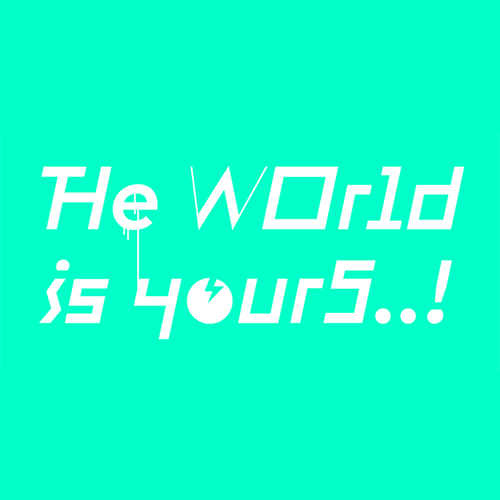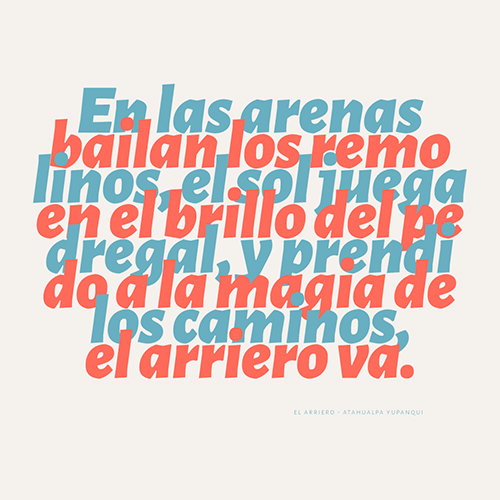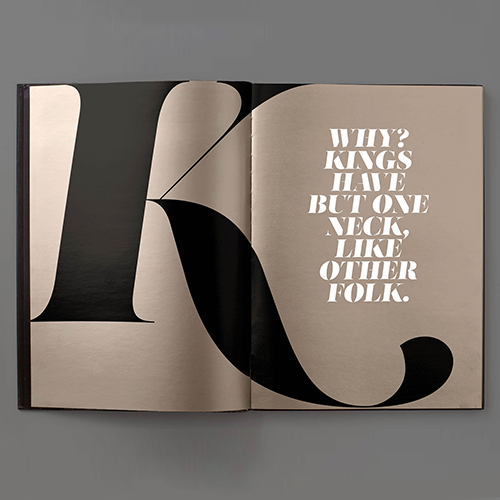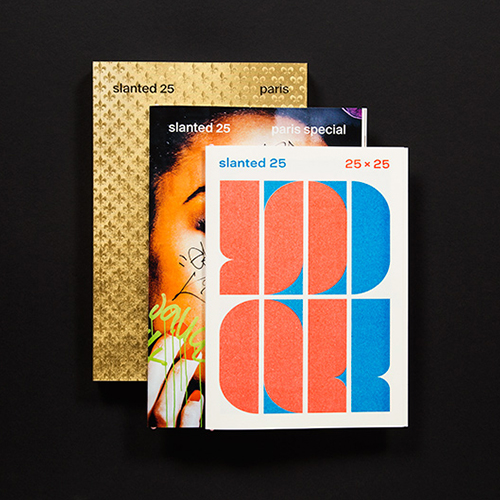
Si teniu pensat passar per la capital, no us perdeu aquesta magnífica exposició on podreu descobrir els millors dissenys tipogràfics de l’any 2015, tant de tipografia aplicada com de disseny de tipus.
La podeu visitar en el marc de Typomad 2015, que se celebra a la Central de Disseny de Matadero Madrid, on s’exposa una selecció de treballs tipogràfics guardonats internacionalment.
La Central de Disseny de Matadero Madrid és un Centre de Creació Contemporània situat a la plaça de Legazpi número 9 de Madrid.
És un espai dedicat exclusivament al disseny en totes les seves formes, on es desenvolupen projectes vinculats al disseny gràfic, el disseny d’interiors i el disseny industrial.
El Matadero disposa d’un ampli espai de referència cultural per a la promoció del disseny i la difusió de propostes i projectes de tota mena.
Aquí es posa en valor la relació entre cultura i economia, integrant-les de manera transversal; així, el disseny gràfic, el disseny de producte i el disseny d’espais s’entenen des d’una perspectiva global, amb la possibilitat d’incorporar-hi valors creatius a l’activitat econòmica.
El centre està gestionat per la Fundación Diseño Madrid i impulsat per l’Asociación de Diseñadores de Madrid (DIMAD), i s’està consolidant tant a nivell nacional com internacional.
Els Premis TDC són atorgats per la prestigiosa associació internacional Type Directors Club de Nova York, fundada el 1946, amb l’objectiu principal de difondre i protegir la paraula escrita formalitzada a través de la tipografia, tant en pantalla com en mitjans impresos.
Entre les diverses activitats de l’organització —cursos, tallers…— es presenta una selecció dels treballs tipogràfics més rellevants, reconeguts i premiats pel jurat internacional segons els criteris de qualitat tipogràfica de l’associació, en les categories de tipografia aplicada i disseny de tipus.
Així doncs, en aquesta exposició podrem veure alguns dels treballs premiats i reconeguts en les categories següents:
1- Tipografies per a aplicació i comunicació
2- Tipografies de nova creació
A més de l’exposició, també es pot assistir a conferències.
Les conferències —Testimonis— són un dels plats forts del festival: grans figures nacionals i internacionals ens parlaran tant del disseny de tipografies com de la seva aplicació en diferents àmbits del disseny, des d’una perspectiva innovadora, diferent i amena.
Jean Baptiste Levée
Toshi Omagari
Ian Party i Emmanuel Rey
Raúl García i Ismael González
Sol Matas
Julia Kahl
Juan Luís Blanco
Jesús Morentin
Diego Dier
Sandrine Nugue
Damià Rotger
Tothom sap la importància d’escollir bé una tipografia per a un projecte: la tipografia no només transmet el seu propi significat, sinó que també comunica cap a fora; la seva forma, pes i mida connecten amb l’espectador més enllà del contingut.
Triar una bona tipografia pot marcar la diferència entre l’èxit, el fracàs o quedar-se a mig camí en un projecte.
Cal entendre el llenguatge del projecte, les seves expectatives, el públic objectiu, el mercat de destinació, i combinar aquesta informació amb els elements de disseny gràfic que s’utilitzaran per assolir els objectius: com es faran servir, com es combinaran i quin llenguatge propi aportaran.
Amb el coneixement de tots aquests elements, podrem assolir el resultat desitjat.